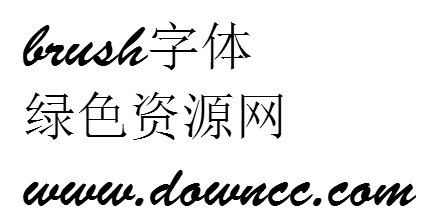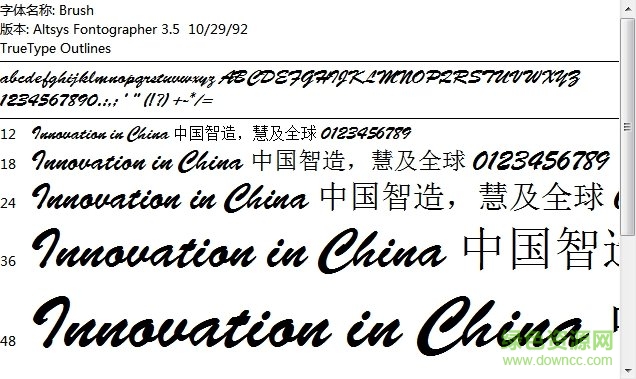
手寫brush字體
brush字體是一款字體連貫、略顯潦草的英文手寫字體,貴族式的書法風(fēng)格讓其顯得更加清秀精簡(jiǎn),讓英文內(nèi)容更具古典氣質(zhì),喜歡的朋友就來綠色資源網(wǎng)試試吧!
手寫brush字體介紹
brush英文啥字體有著超酷的手寫連筆書法風(fēng)格,如果不分散字距,每個(gè)字母之間就像連在一起一樣,讓行文都透著一股清爽干練的沉穩(wěn)氣息。
brush字體
brush字體有著十分簡(jiǎn)明隨意的手寫字體風(fēng)格,連貫的行文讓文字更加流暢,給你的平面設(shè)計(jì)、書面排版、印刷設(shè)計(jì)等增加不少特色韻味。